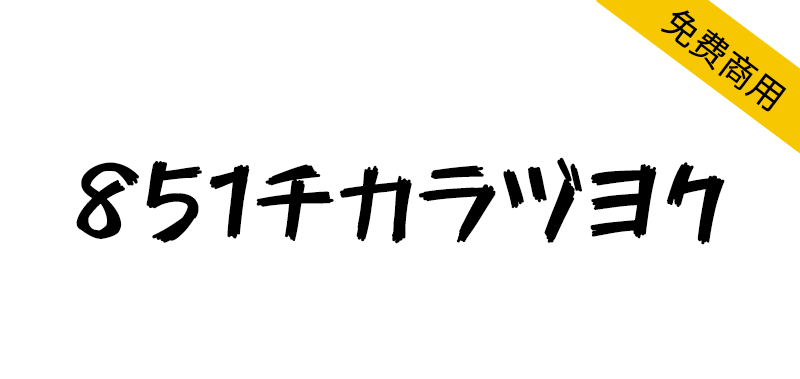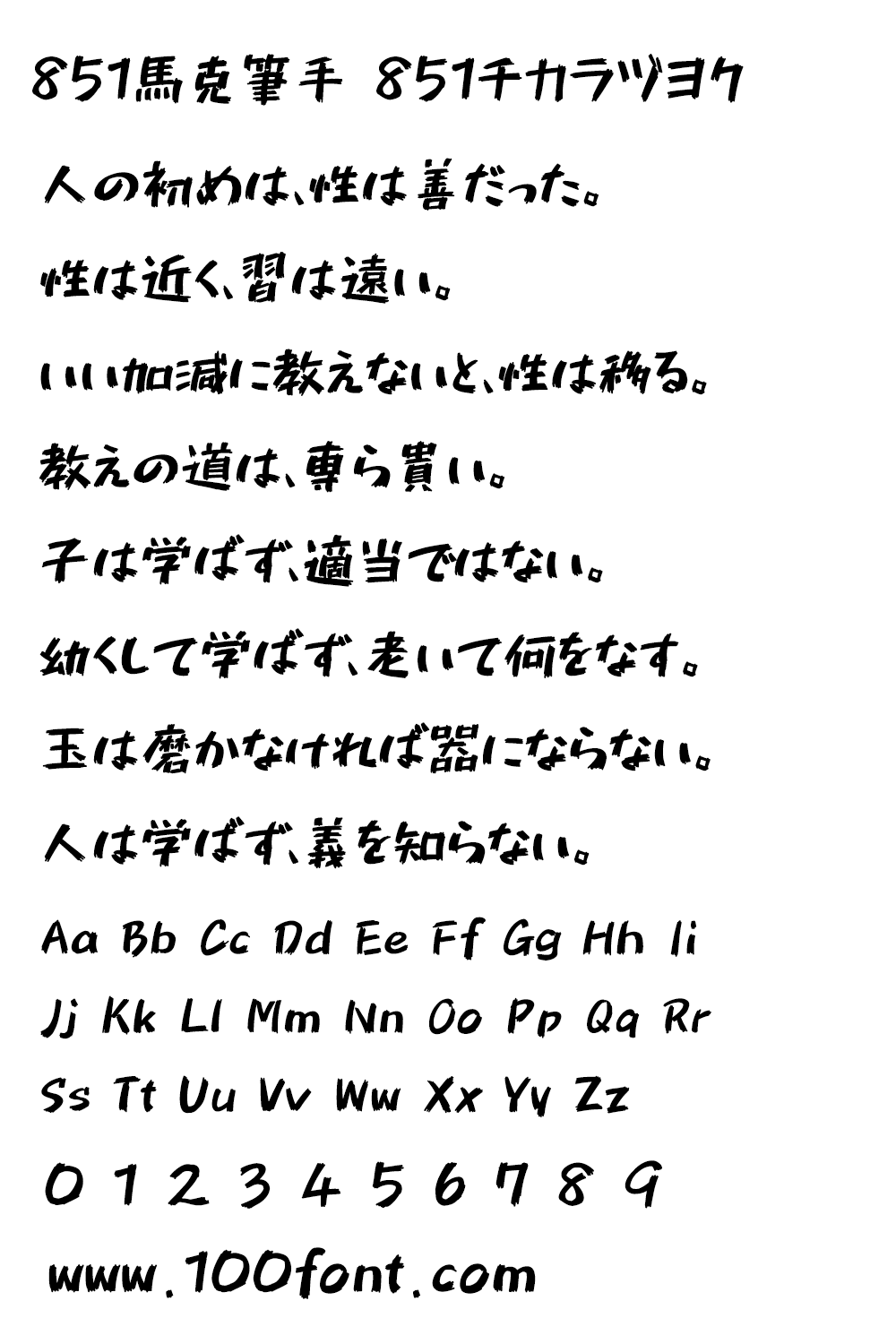
851马克笔手写体(51チカラヅヨク)是日本设计师 8:51:22 pm 设计的一款马克笔手写体,横细竖粗,行笔飘逸,当前字符数:3859个字符(不包括空格)。
对应文字:平假名、片假名、拉丁文字(英语)、数字、符号(少许)、汉字(常用汉字+少许)
注意:这款字体适用于繁体和日文,不适用于简体中文,容易缺字。